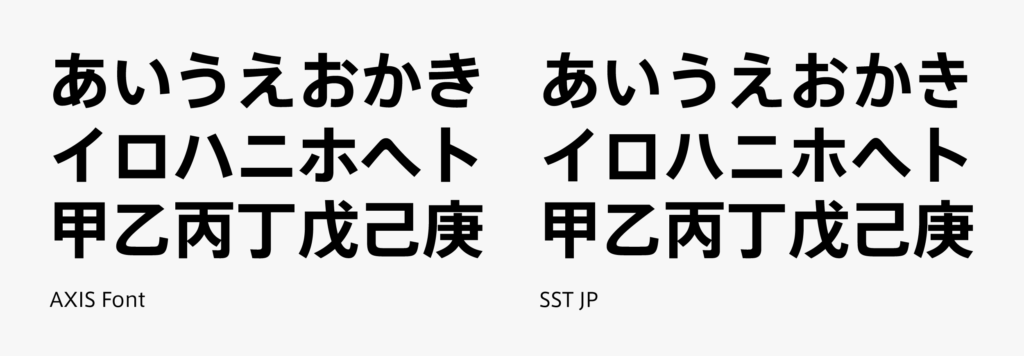
漢字と仮名の組み替え02「SST JP」
今回はタイププロジェクトの漢字仮名組み替え事例としてSST JPをご紹介します。
SSTは、ソニー株式会社とMonotype社が共同開発したコーポレートフォントで、ソニーの製品パッケージや名刺などで使用されています。タイププロジェクトはMonotype社より委託を受け、和文フォントであるSST JPを開発しました。ソニーに提示された「プロダクト感」をデザインに展開したオリジナルの仮名を新たに制作し、漢字はAXIS Fontを組み合わせています。
現代の日本語表記で仮名は文章のうち6~7割を占め、そのうえ漢字より必要なグリフ数がずっと少ないので、オリジナル仮名制作は限定的な作業でありながら組版全体のイメージ変えに効果的です。